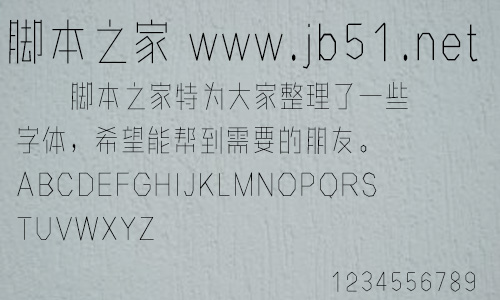
站酷型麗體細(xì)體light是由站酷字庫出品的藝術(shù)字體,這款字體筆觸較為纖細(xì),書寫端正,字體略顯細(xì)長(zhǎng),具有很好的視覺感,適合應(yīng)用于藝術(shù)設(shè)計(jì)、平面宣傳設(shè)計(jì)、網(wǎng)頁設(shè)計(jì),書法字帖等領(lǐng)域。